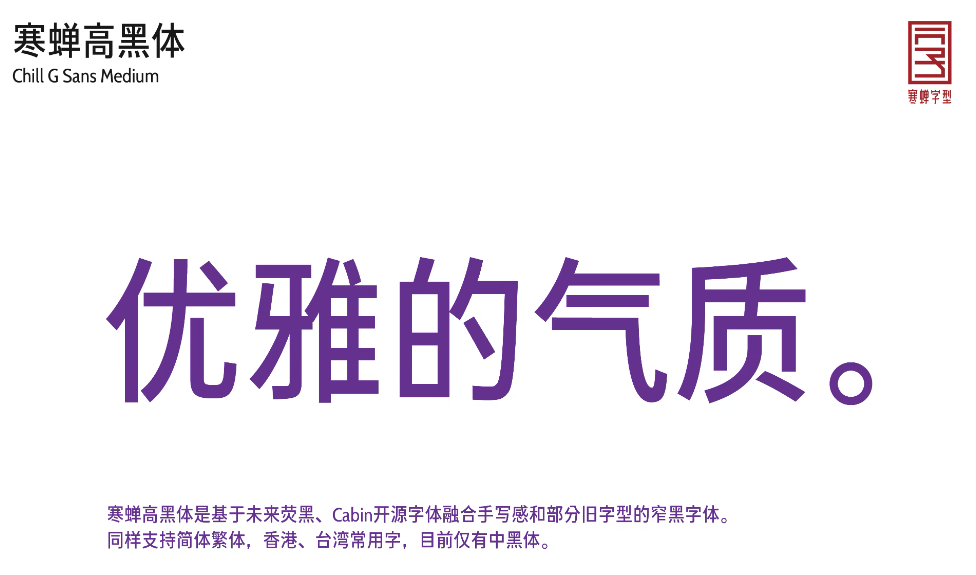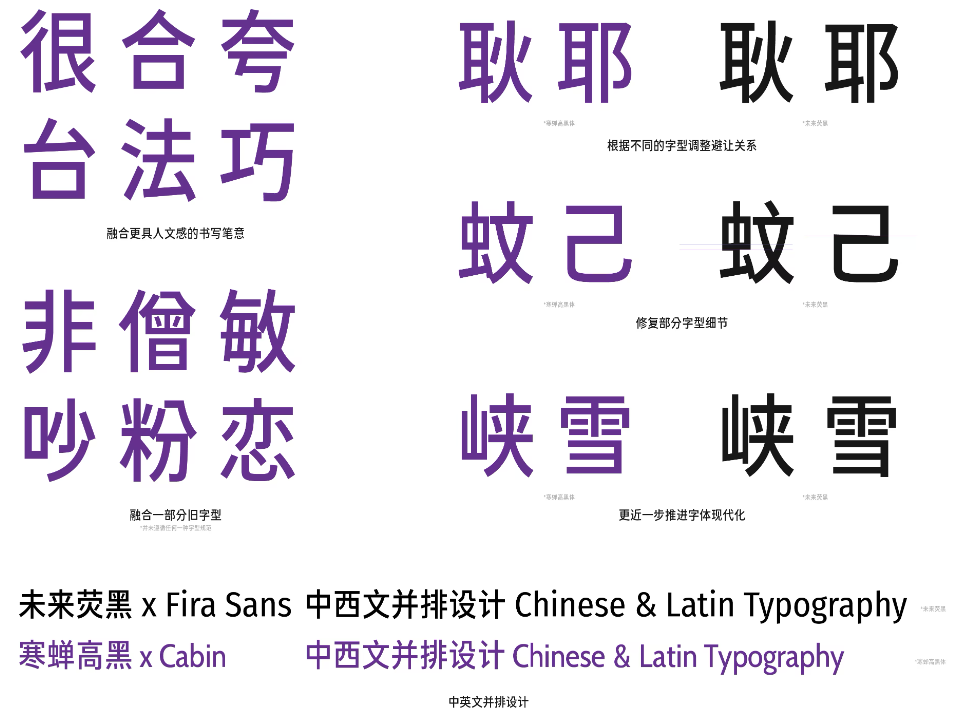
寒蝉高黑体(Chill G Sans)是一款融合手写感和部分旧字型的可免费商用的窄黑中文字体。可以算是未来荧黑 的升级版。由于未来荧黑是基于思源黑体 的算法建模参数化调整,没有使用字体设计软件,所以寒蝉高黑体在这一基础上手动检查修复近8000个字符轮廓,弥补了未来荧黑字型轮廓调节不到位的问题。而未来荧黑使用的 Fira Sans 英文搭配,寒蝉高黑体则改用成了开源的 Cabin 作为英文部分。
虽然目前寒蝉高黑体仅提供中黑体(Medium),但可以覆盖简体中文、繁体中文、香港台湾常用字、日文总计31876个字形。再加上窄黑结构和手写风格的融合,让它可以满足多种场景的排版需求,比如标题排版、正文排版、包装设计、字幕制作等。